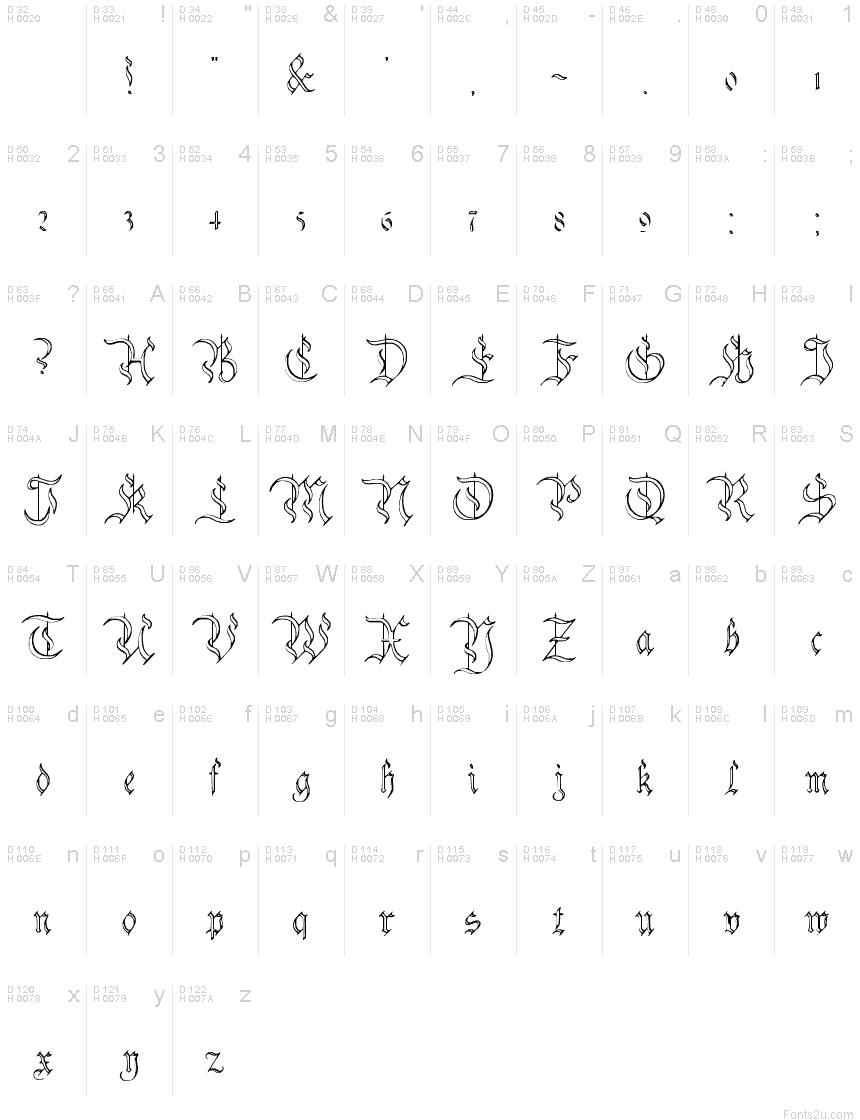
Krój Charterwell No4 od PJL to darmowy gotycki font nawiązujący do stylu średniowiecznego. Jego litery wyglądają, jakby zostały wydrapane metalową stalówką – wysokie, drapieżne pociągnięcia, haczykowate zakończenia i wąskie oczka nadają każdemu słowu mroczną, ceremonialną aurę. Rytm jest ciasny i pionowy, dzięki czemu nawet krótki nagłówek zyskuje gęstą, wyrazistą formę, która natychmiast przywodzi na myśl klimaty fantasy, metalu czy historycznych dramatów.
Dzięki Charterwell No4 nagłówki nabierają charakteru w tytułach gier RPG, na okładkach książek fantasy, logotypach zespołów, szkicach tatuaży, plakatach średniowiecznych jarmarków czy zaproszeniach na wydarzenia w stylu gotyckim. Ten darmowy font najlepiej prezentuje się w dużym rozmiarze i z nieco szerszym światłem między literami, co pozwala wybrzmieć jego ostrym łukom i kolcom. W tekście głównym zestaw go z prostym, nowoczesnym krojem bezszeryfowym, aby zapewnić czytelność, podczas gdy Charterwell No4 zadba o nastrój.